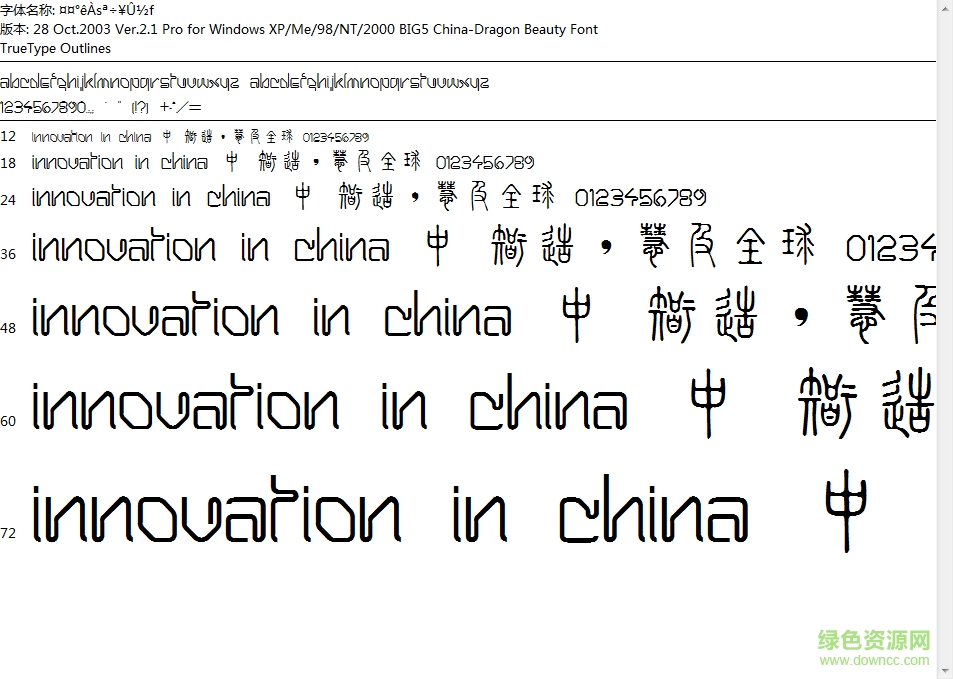
idjinzhuan 字體又叫中國龍金石篆字體,字形繁復(fù),難以辨認(rèn),就像篆刻出來的字體一樣,具有極大藝術(shù)欣賞價值,多用于美術(shù)設(shè)計方面,歡迎需要的朋友來綠色資源網(wǎng)免費下載!
【小篆】
小篆較之大篆,形體筆畫均已省簡,而字?jǐn)?shù)日增,這是應(yīng)時代的要求所致。從古文到大篆,從大篆到小篆的文字變革,在中國文字史上具有劃時代的意義,占有重要地位。
【大篆】
漢字的古代體之一。它的名字見于漢代著作,與“小篆“對稱。廣義指“小篆”以前的文字和書體,包括甲骨文、鐘鼎文、籀文和六國文字等;狹義專指周宣王太史籀厘定的文字,即'籀文'。'大篆'的代表作品,有《石鼓文》和《秦公簋》銘文等。